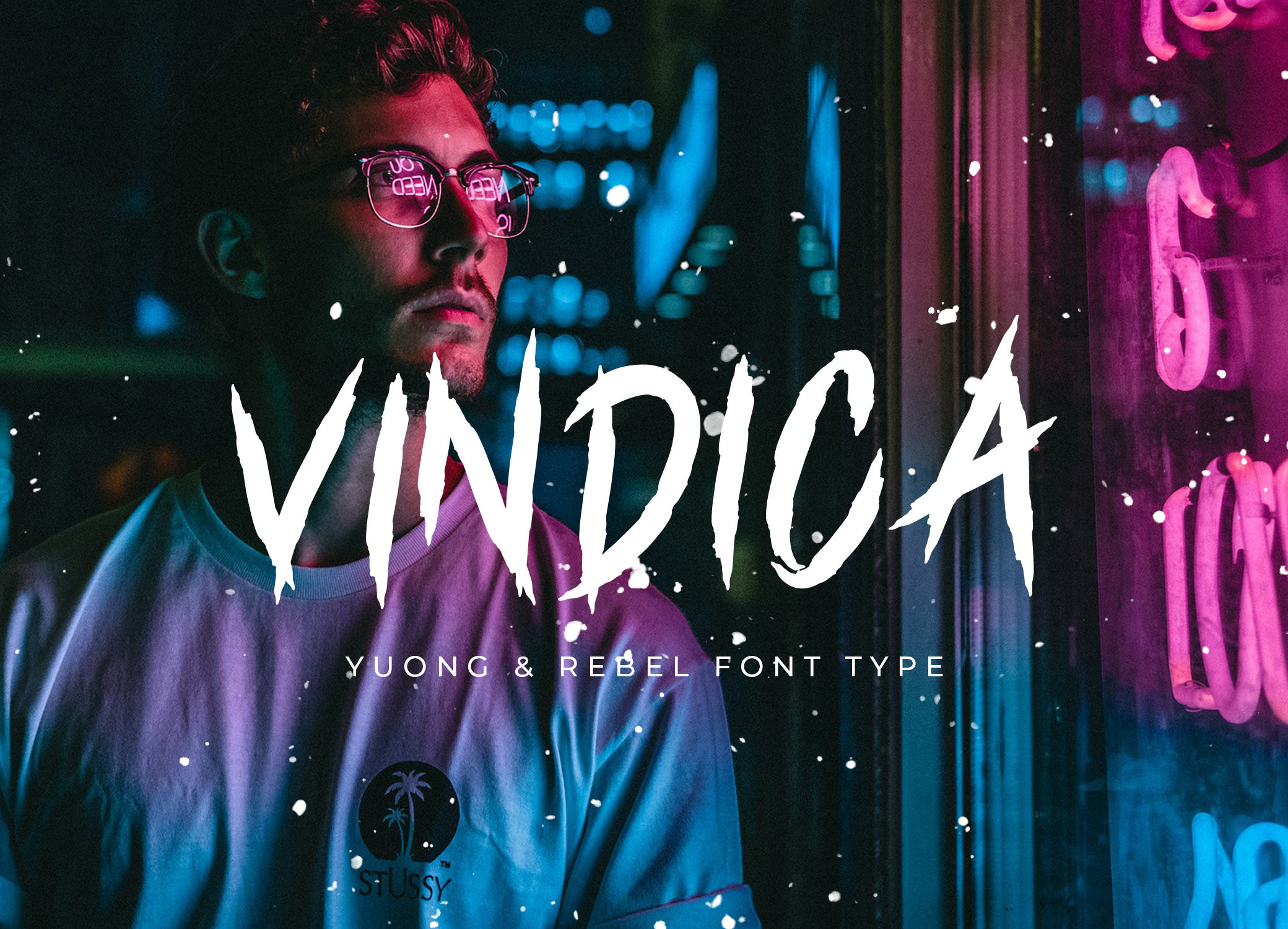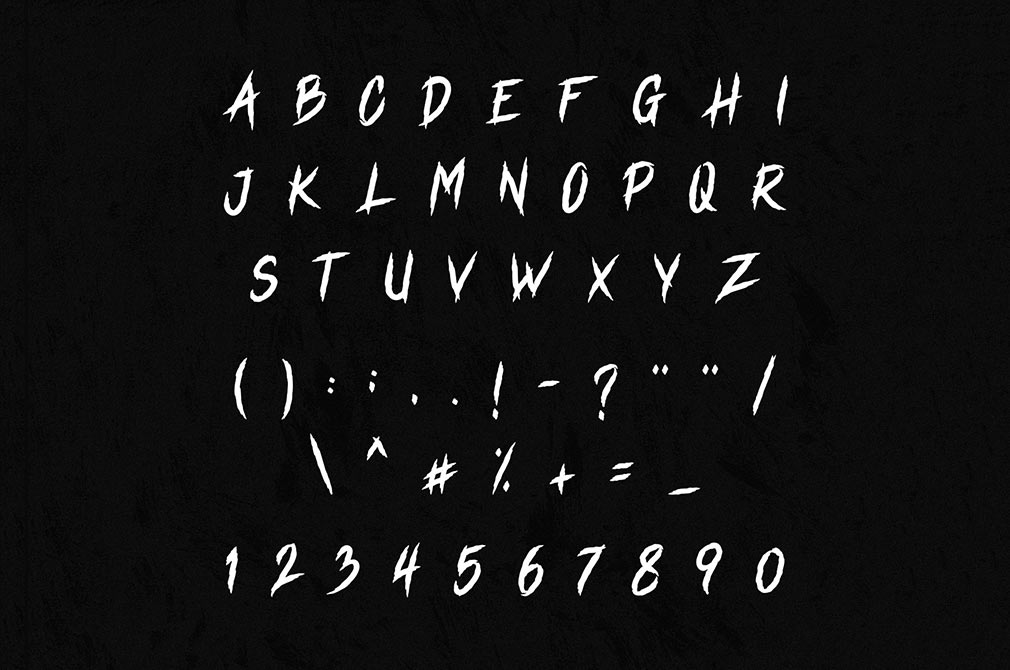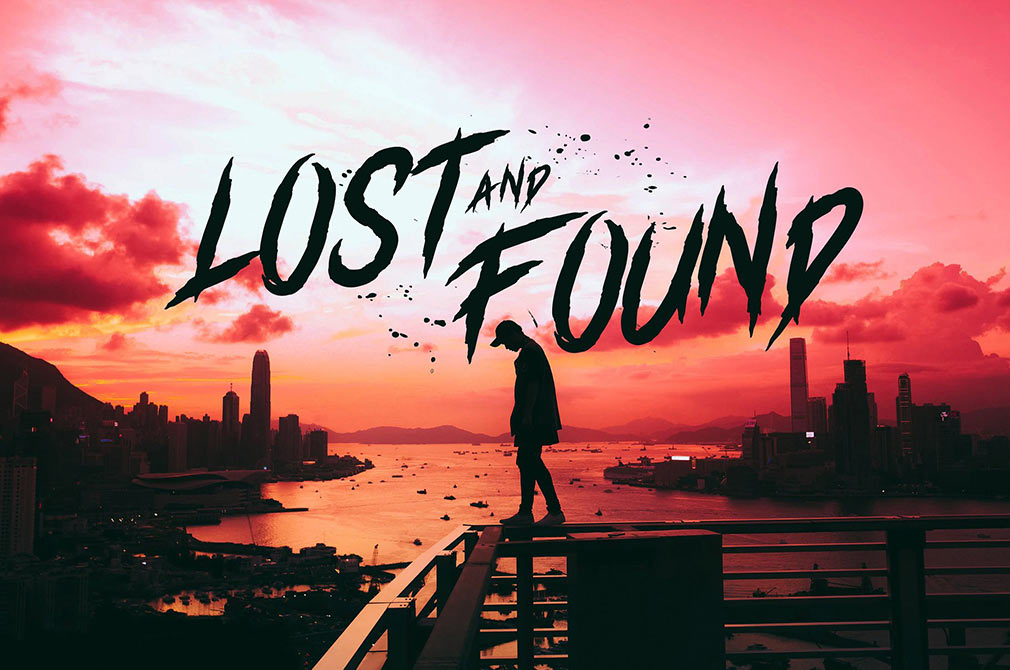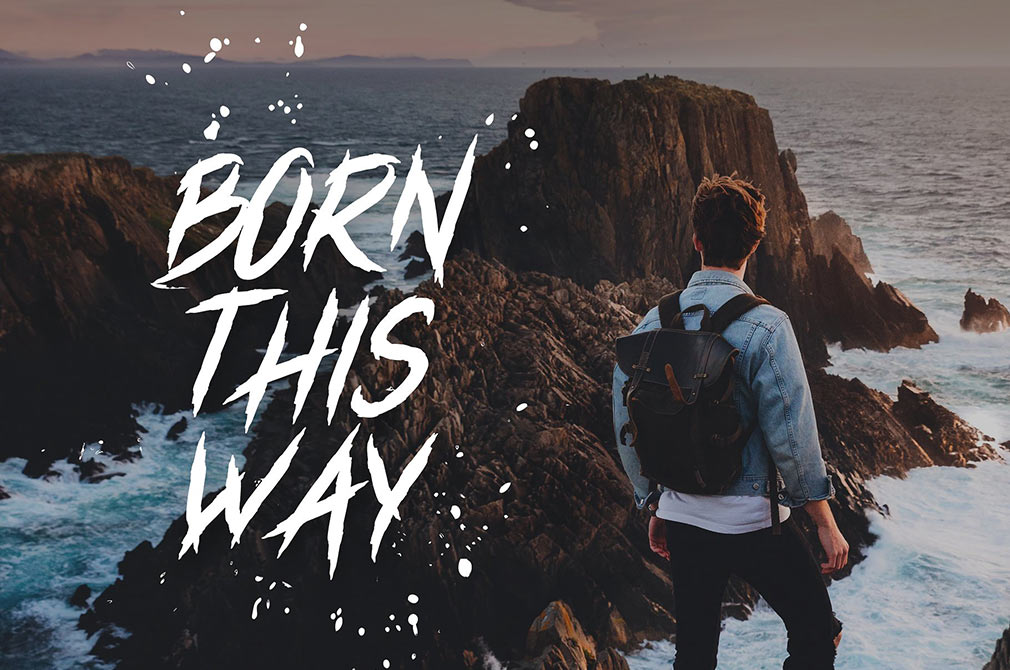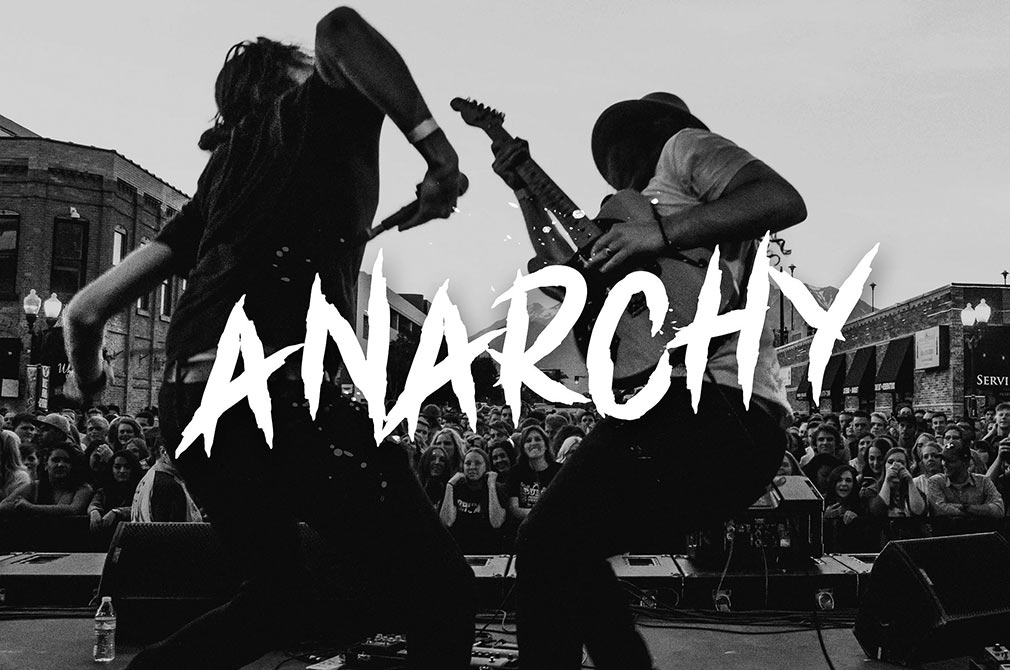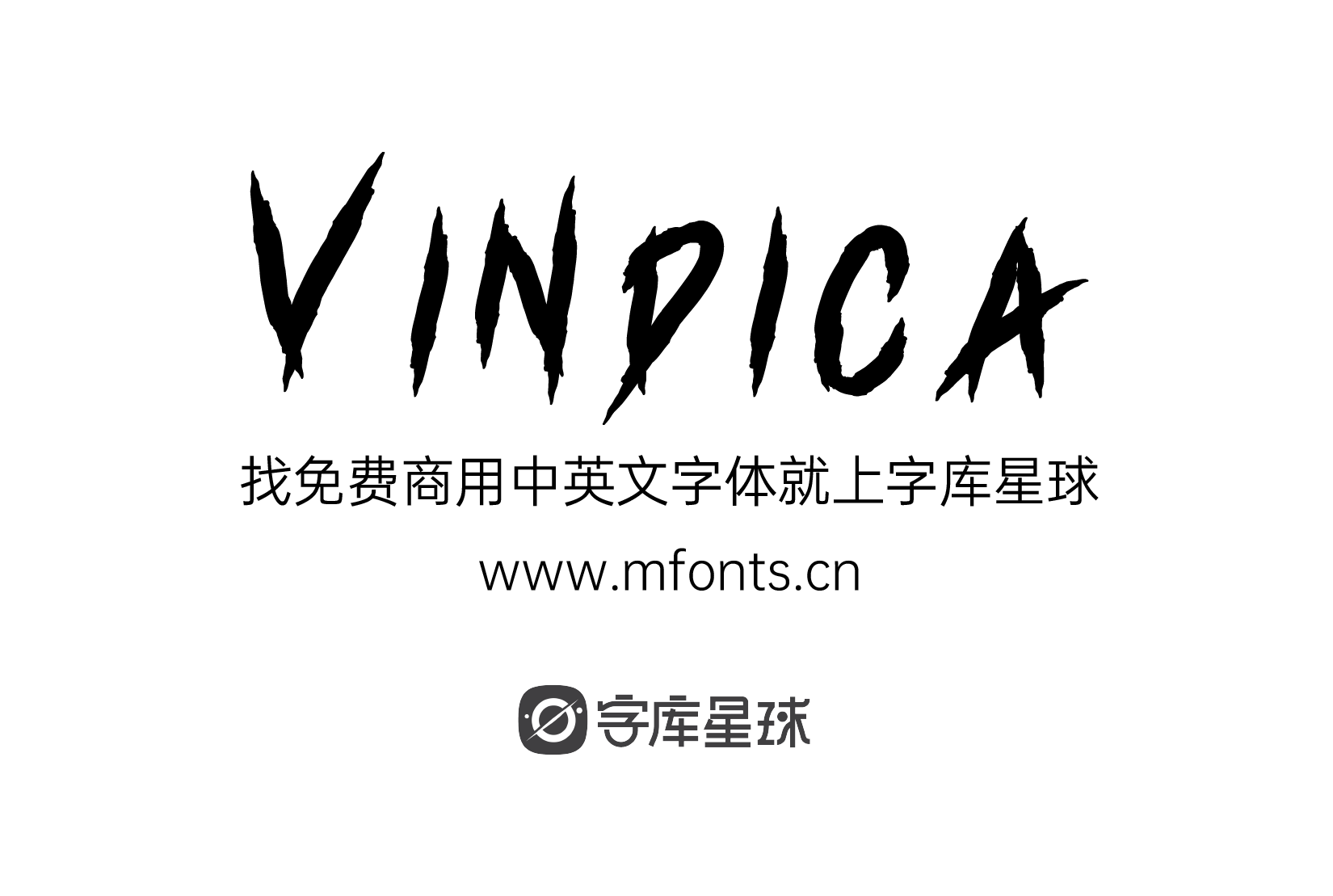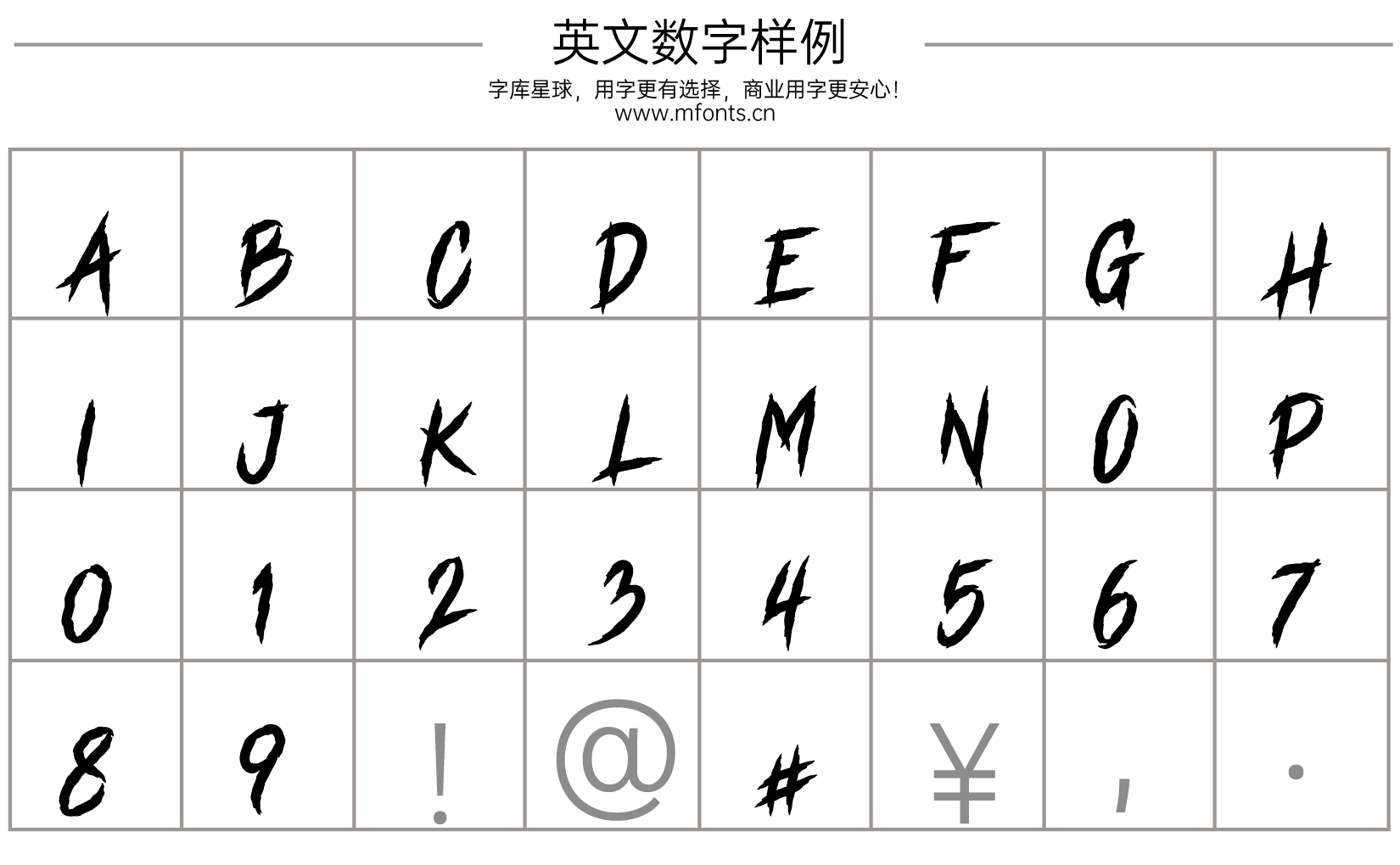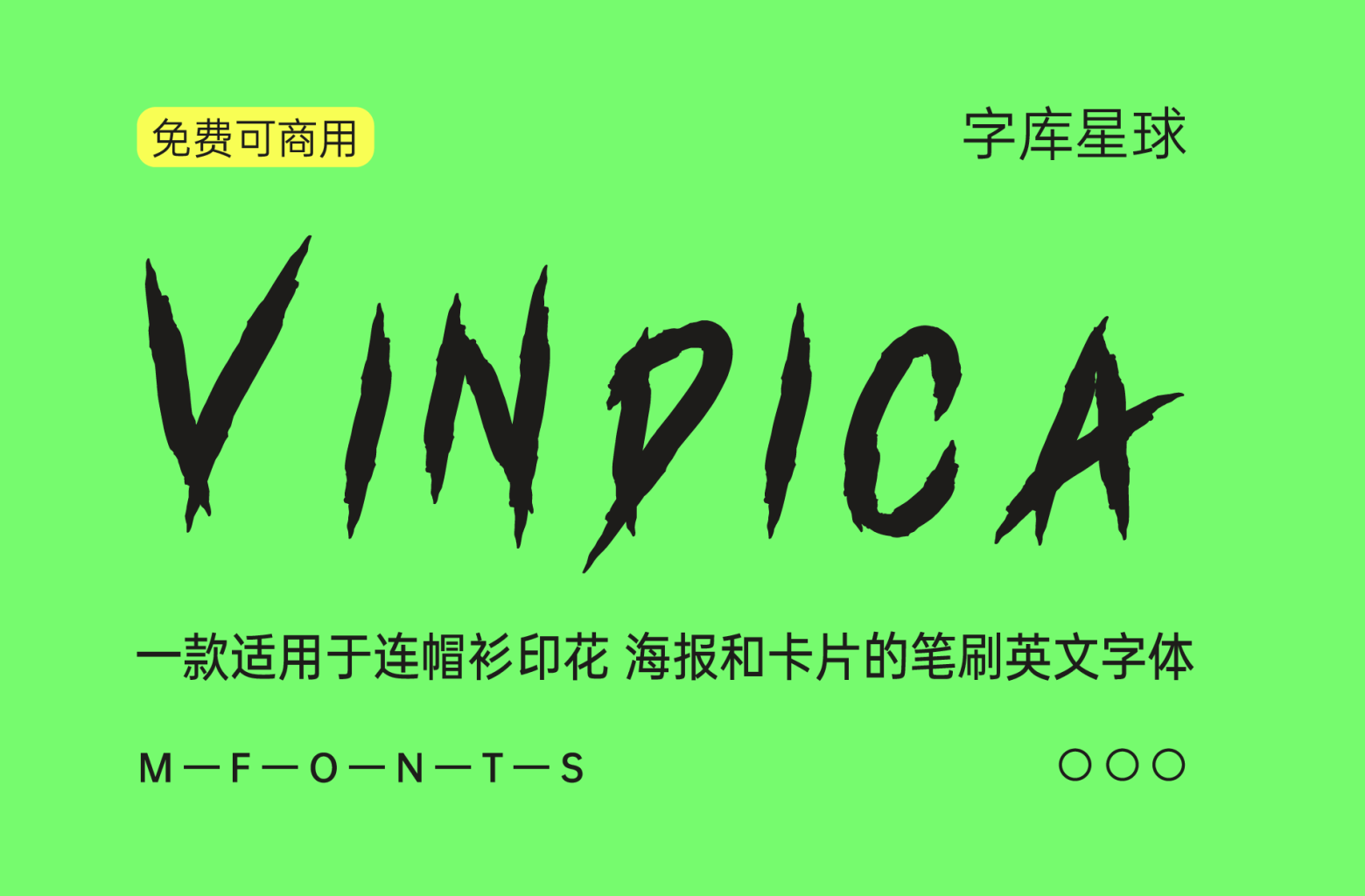
这种笔刷字体就像空气嬉戏着你的头发,如此自由而梦幻。它的每一笔都蕴含着绝对的能量,能让任何作品都值得喝彩。
Vindica 对字体设计充满热爱,可以匹配所有可能的支持字体,并通过其表现形式和大量字形传达正确的情绪。将其用于连帽衫印花、海报和卡片,或补充您的网站或应用程序设计,您一定会喜欢最终的图像!